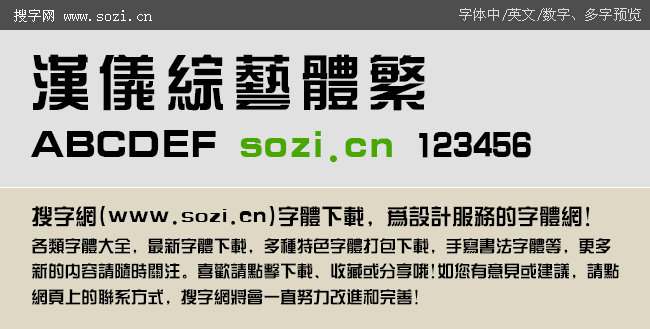
漢儀綜藝體繁
搜字網(wǎng)提供一款漢儀綜藝體繁下載。綜藝體是黑體的一種變體,也是藝術(shù)字的一種。特點(diǎn)是筆劃更粗,盡量將空間充滿。同時(shí)為了美觀,對(duì)拐彎處的處理較為圓潤。適用于廣告、報(bào)刊等的標(biāo)題及海報(bào)展板等設(shè)計(jì)場合使用。